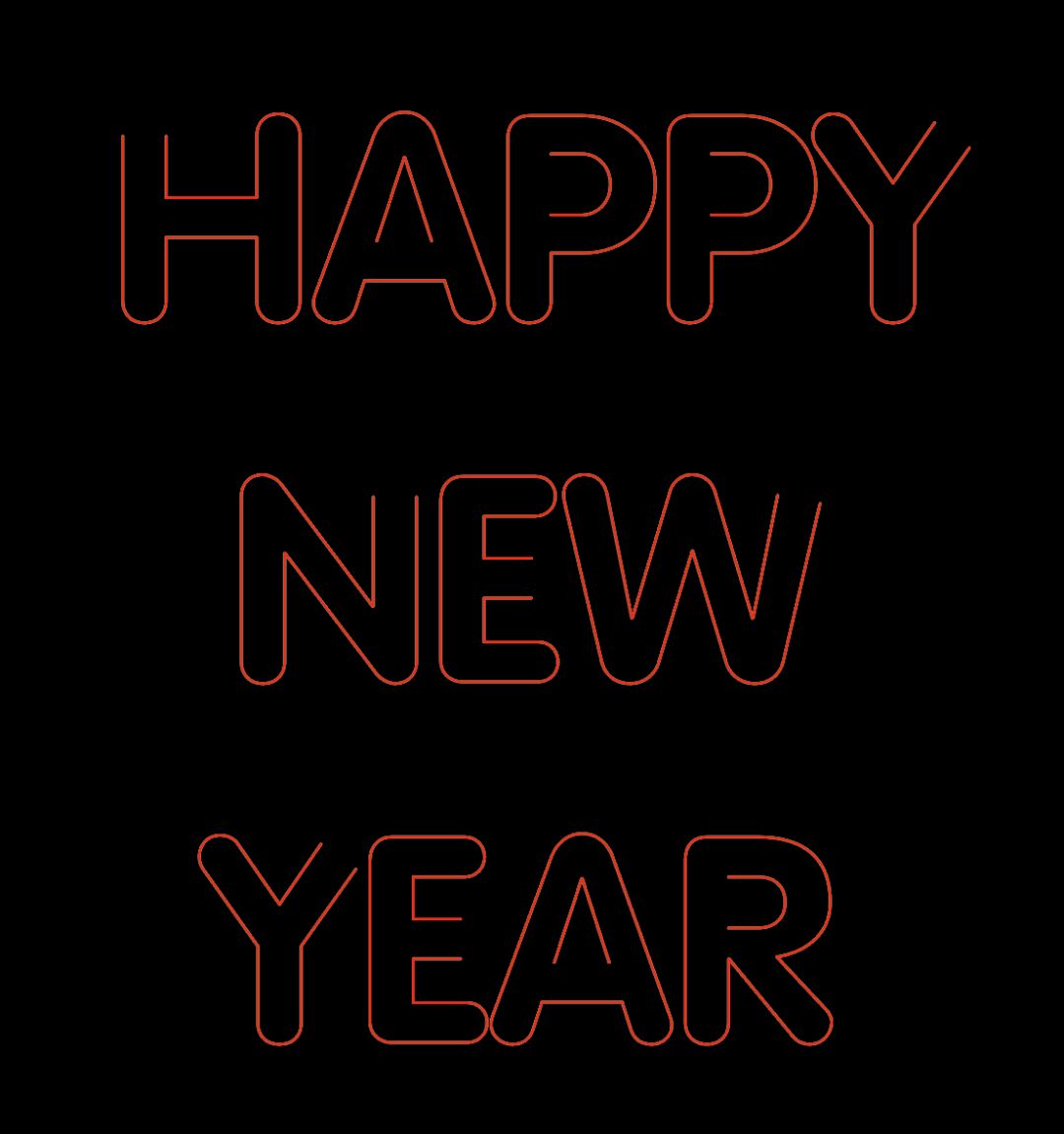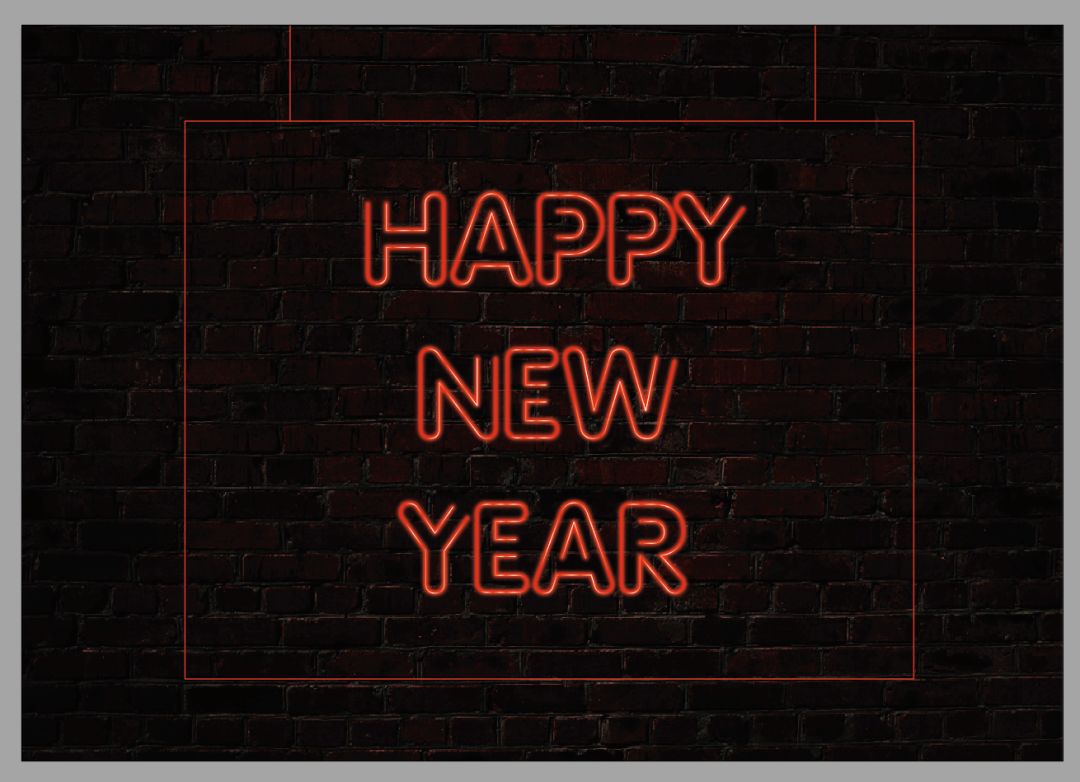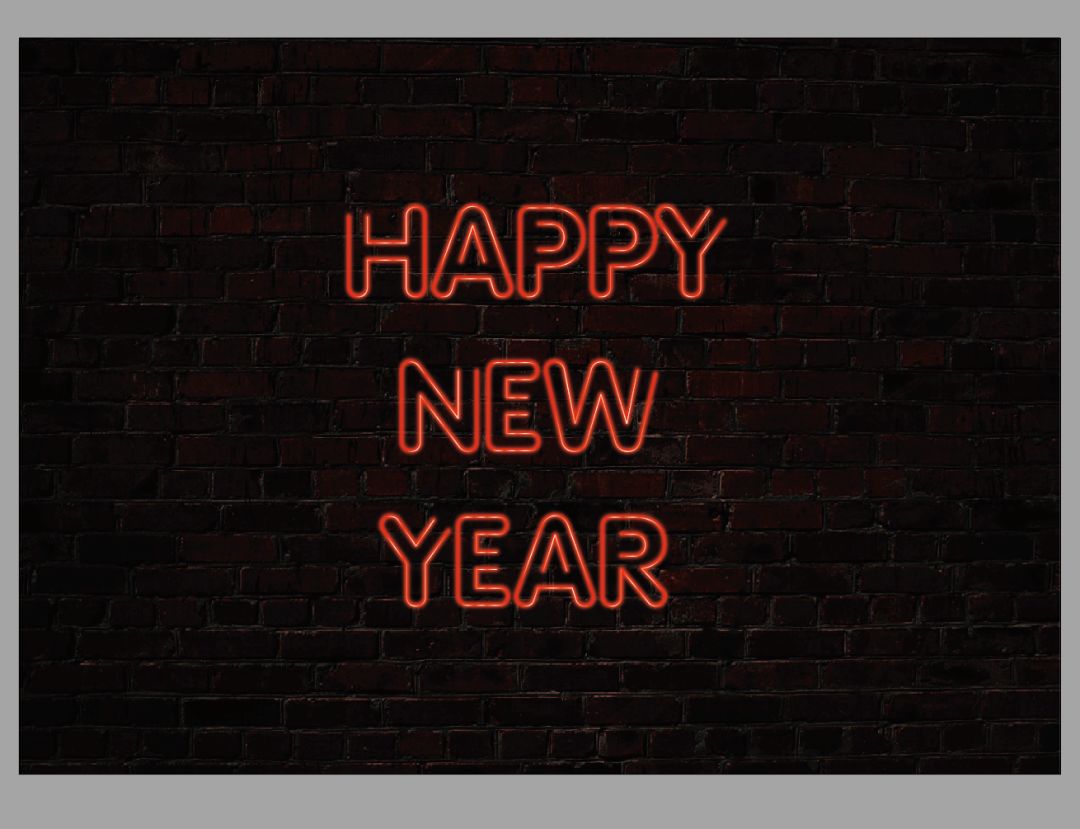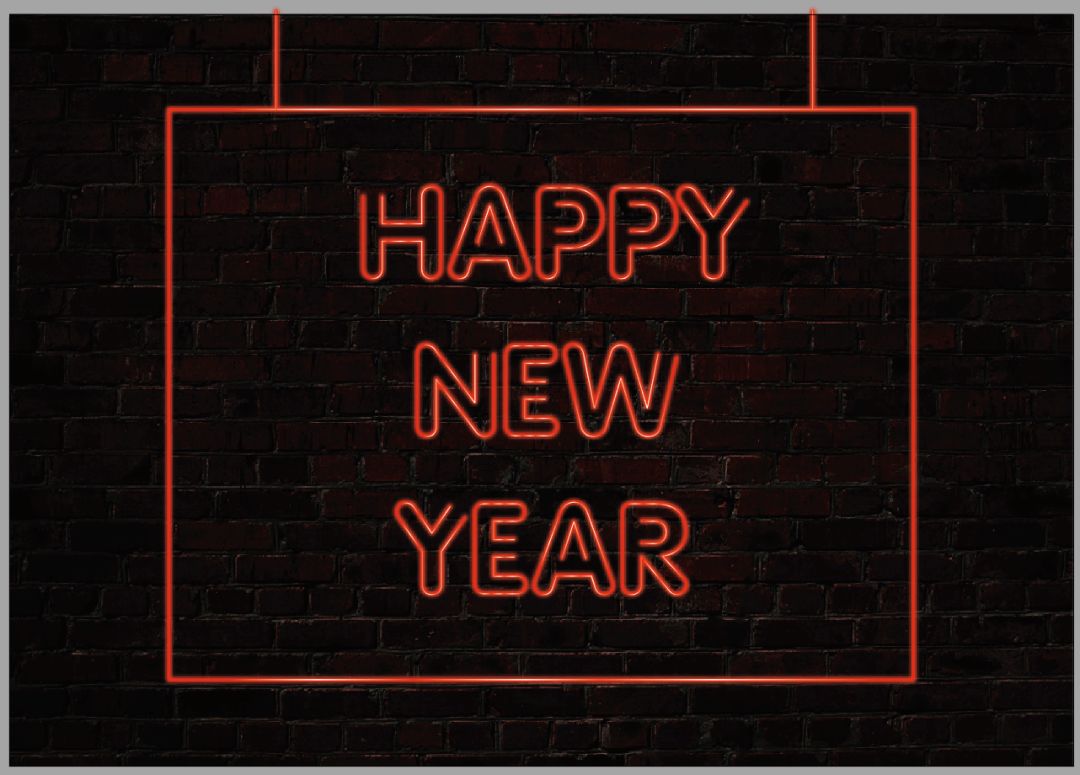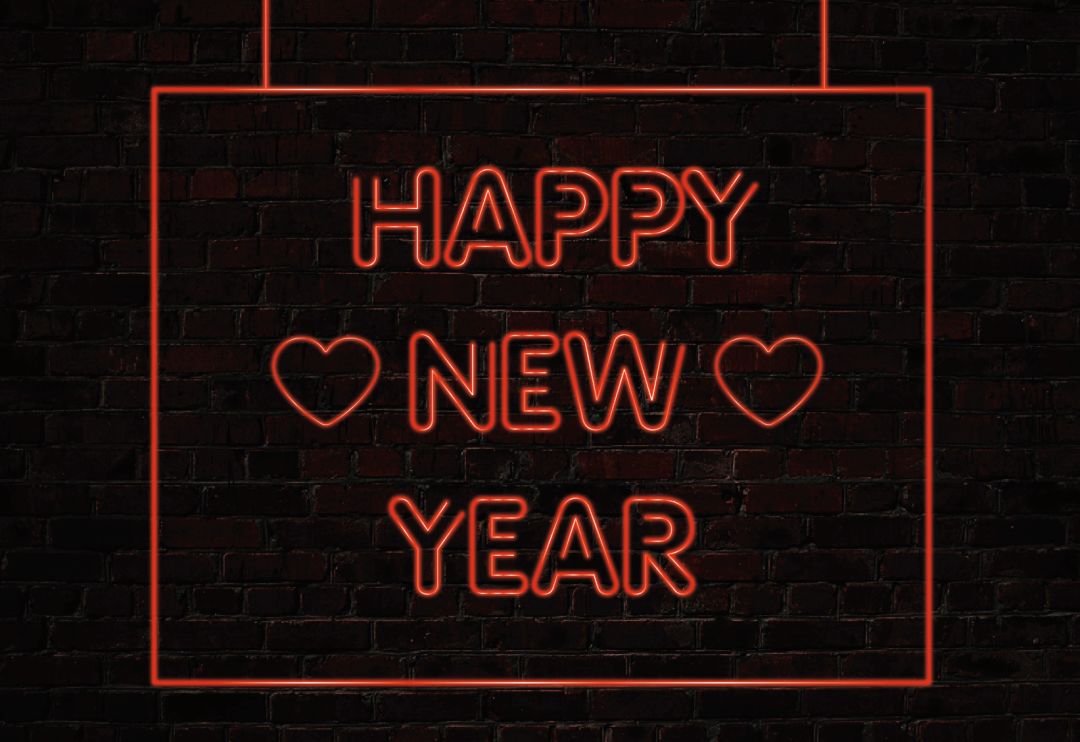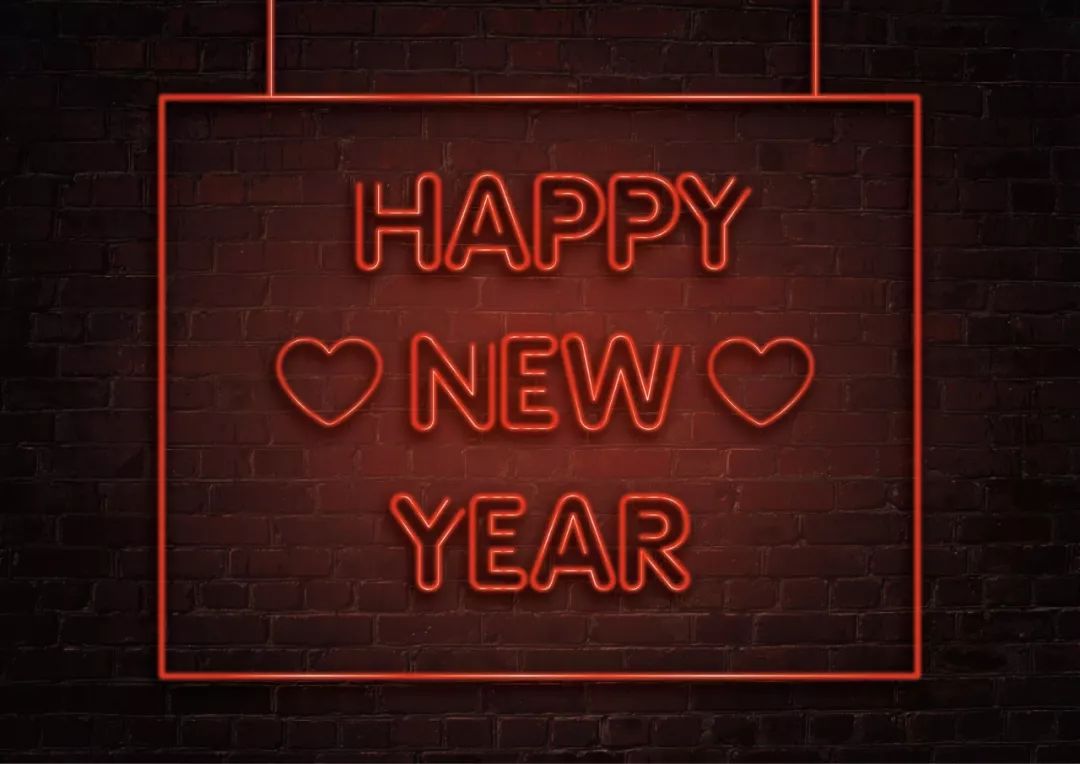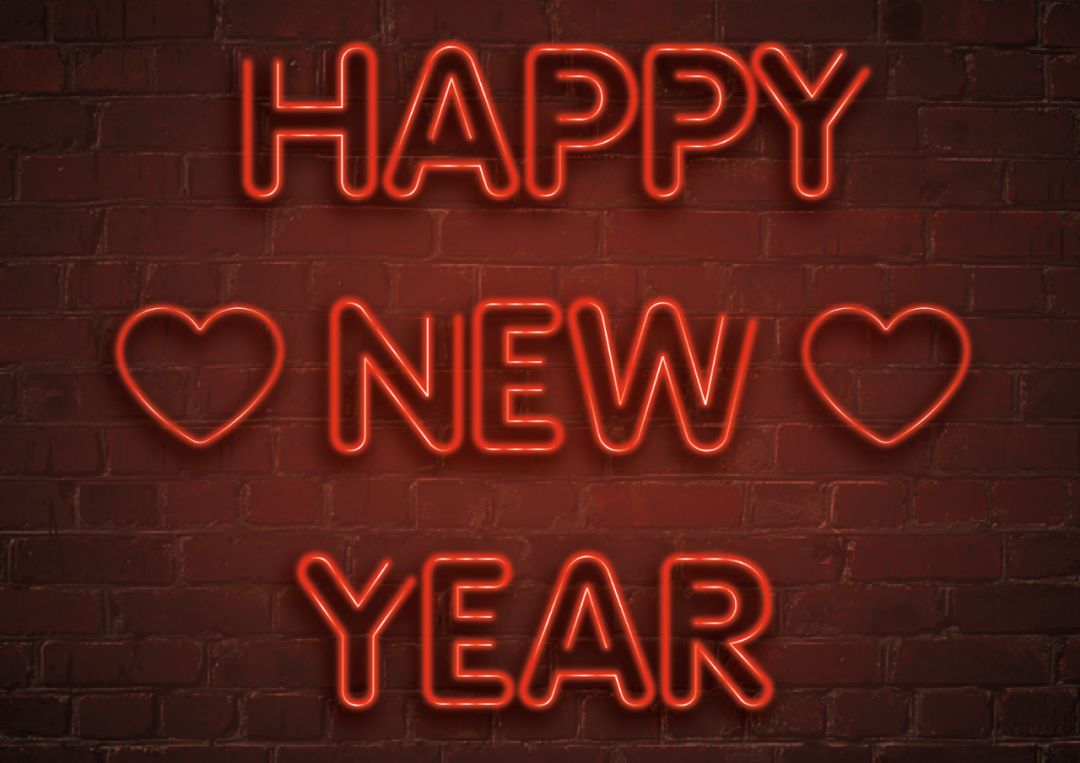
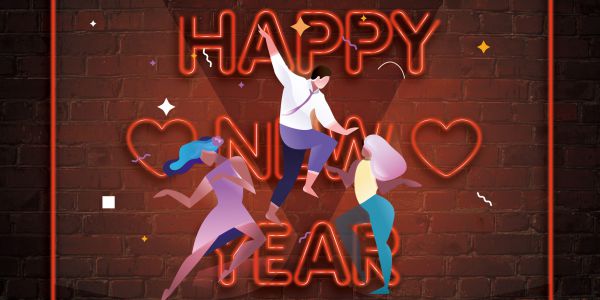
先P一个轰趴场景
霓虹灯效果的字体,最适合轰趴,感觉一切都很神秘,我们今天来做一个。打开AI,输入“HAPPY NEW YEAR”,打开字由,选择相对圆润的字体,我的是VAG Rounded Std。
选中文本,水平垂直居中,对齐。
将填色改为描边,并点击鼠标右键,创建轮廓。
如果字体没那么圆润,也可将端点改为圆头端点,边角改为圆角连接。
取消编组,变为单个字母可编辑状态, 点击选择工具,选择想要删除的笔画,进行删除。
删除后效果如下,为了热闹,特意选择红色,你也可以选择其它亮色。
点击对象——编组,按住ALT键进行复制。
我复制了5个,并加大了黑色背景板的长度。
选中第一组,点击效果——模糊——高斯模糊,像素为1。
选中第二组,点击效果——模糊——高斯模糊,像素为2。
以此类推,第三组,像素为4。
第四组,像素为6。
将第四组的描边加粗至4pt。
将第三组的加粗至2pt。
以上步骤完成后,就要进行叠加了,按第一组到第四组的顺序,没有进行模糊的第五组,放到最上面。
效果如下,这时候感觉灯管少了一些光泽,该怎么做呢?
将没有进行模糊的第五组拖出来,点击渐变工具。
点击吸管工具,按住Shift进行取色,将渐变条变成如下红白相间的样子。
渐变好后,再将其叠回原位,就会有光泽的感觉啦~
点击鼠标右键——编组,让字体居中,方便移动,并插入已经选好的背景图(越暗越好)。
基本完成,可还是觉得有点空?
用矩形工具和钢笔工具,加一个悬挂的边框,招牌感马上有了。
这里又要运用刚才做字的方法了,你可以再复习一遍。先复制5个,将第一个描边加粗至4pt,高斯模糊,像素为6。
第二个描边加粗至2pt,高斯模糊,像素为4。
第三个,高斯模糊,像素为2。第四个,高斯模糊,像素为1。
选中五个,运用刚才的渐变素材,得到如下效果。
最后来一个五层汉堡叠加~
心形的装饰,同样如上操作~
到这一步,应该结束了吧,不过有强迫症的我,觉得还应该去ps处理一下,复制色号E83518。
打开PS,新建自定义画板,并用圆形工具绘制一个椭圆形。
点击滤镜——模糊——高斯模糊,根据自己的绘制的大小调整数值,我调到了270像素。
关掉背景图层,储存为png。
将png拉到AI当中,不透明度调至70%。
选中所有灯管效果的素材,点击效果——风格化——投影,根据自己的需求,调整数值。
最终就是这样了,还挺有质感的,感觉像玩那个电棒闯关的游戏!